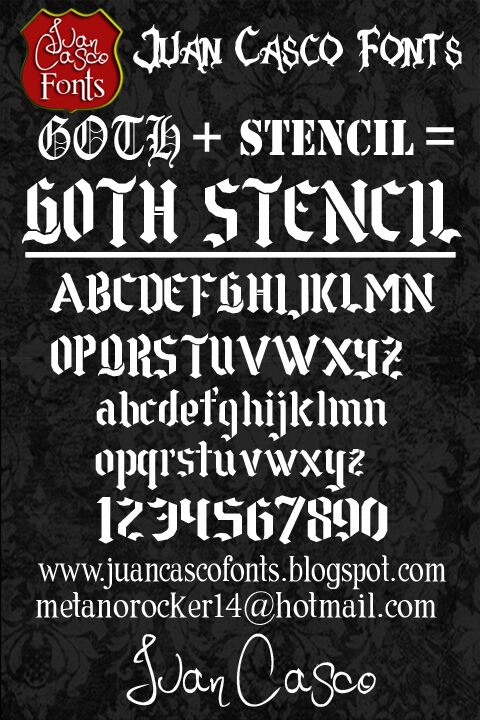
Goth Stencil autorstwa Juana Casco to darmowy gotycki krój typu stencil, zbudowany z surowych, kanciastych pociągnięć, spiczastych koron i ostro wyciętych przerw, które przerywają kształty liter. Jego przełamane łączenia nadają wielkim literom rzeźbioną, architektoniczną sylwetkę.
Ilustracje średniowiecznych zbroi, okultystycznych symboli lub scen mrocznego fantasy mogą nawiązywać do tych wyszczerbionych form, dzięki czemu napis sprawdzi się na okładkach gier, plakatach muzycznych i grafikach na gadżety z teatralnym zacięciem. Najlepiej sprawdza się w brandingu branży rozrywkowej i promocji wydarzeń, gdzie gotyckie kształty mogą stać się częścią herbu, insygniów scenicznych lub ilustrowanego emblematu, zamiast służyć jako neutralny tekst na ekranie.
Połączenie stylów stencil i gotyckiego.